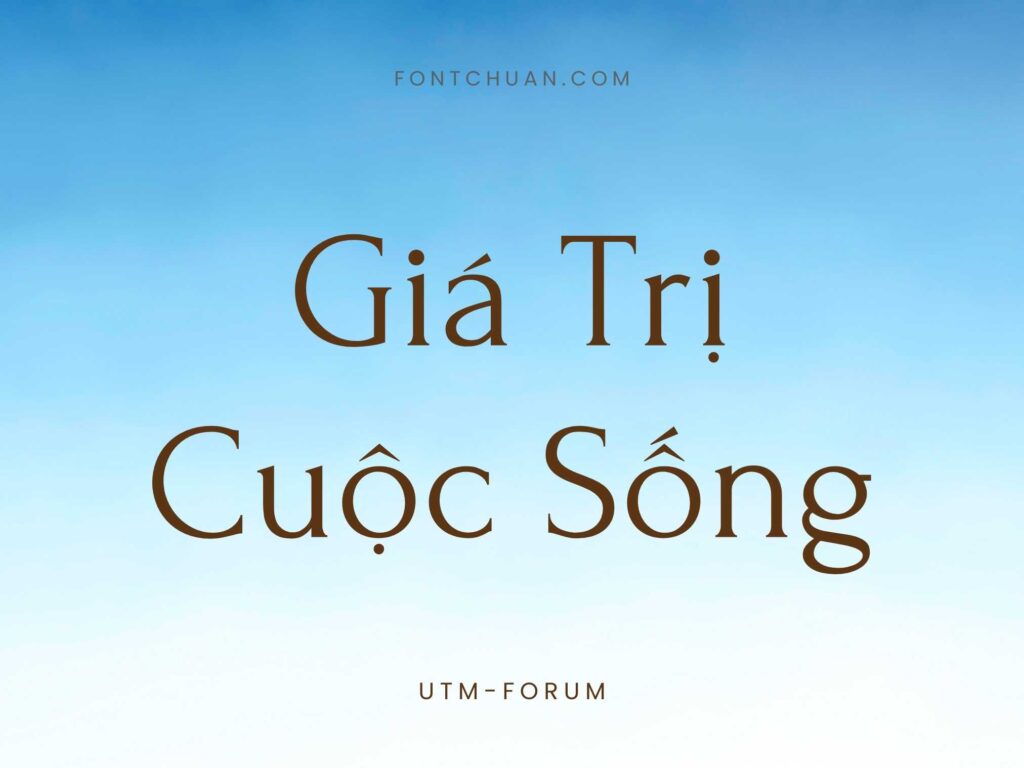
Font UTM Forum Việt Hóa là một kiểu chữ serif cổ điển, mang phong cách thanh lịch và sang trọng. Với các đường nét thanh mảnh, tỷ lệ cân đối và độ thoáng rộng, font này là sự lựa chọn lý tưởng cho các thiết kế mang phong cách truyền thống, lịch sự và chuyên nghiệp.